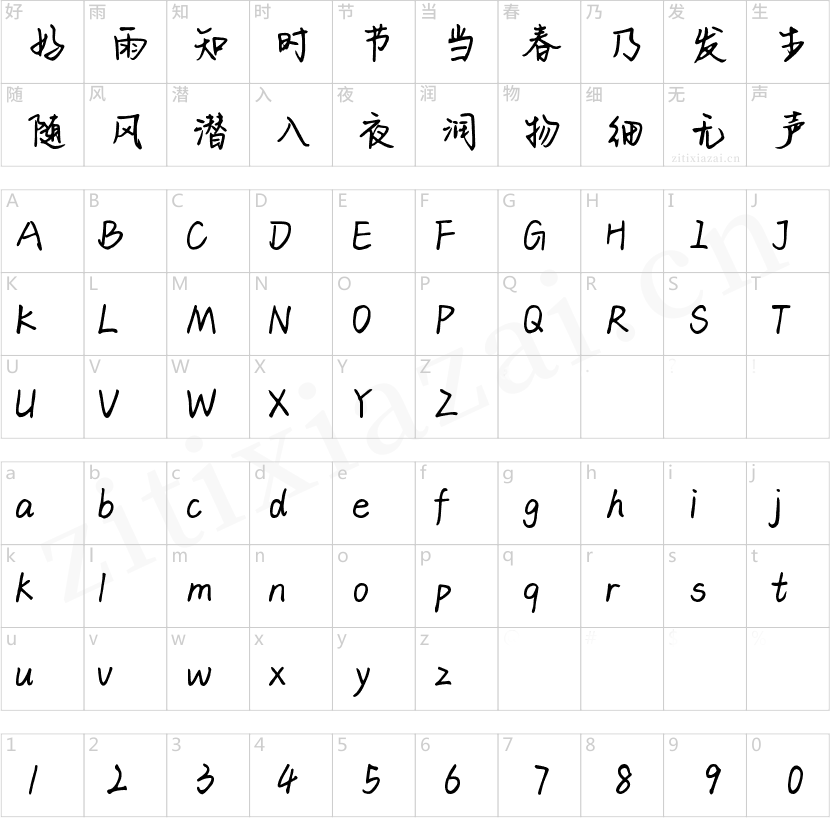
Aa魔鬼中的天使
Aa魔鬼中的天使字体
Aa魔鬼中的天使是一款非常具有艺术性的字体,它的设计灵感来源于对古典艺术的研究,同时又融入了现代字体设计的元素。字形优美,笔画粗细变化自然,给人以大气、典雅的感觉。Aa魔鬼中的天使是一款既传统又现代的字体,它的设计充满艺术感,美观大方,实用性也非常强。无论是对于设计师还是对于普通读者来说,都是一种非常不错的字体选择。Aa魔鬼中的天使适合用于具有艺术感的场合,比如海报、宣传单张、书籍封面等。由于其字形流畅且具有动态感,也适合用于大量的文本排版,如报纸、杂志等。